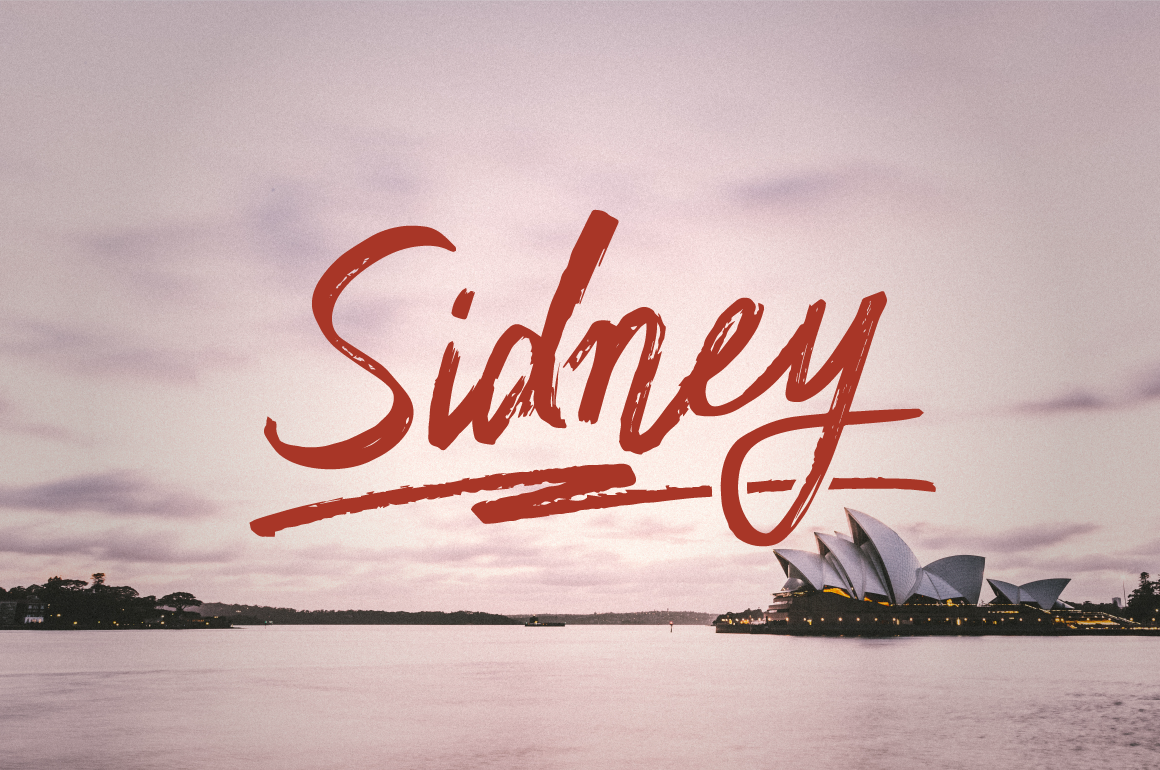
A Sidney Script Font é uma opção única para designers que buscam um estilo elegante e moderno, com uma personalidade intrínseca. Suavemente irregular, esta tipografia oferece 300 formas de letra, ligações e letras extras, criando um universo incrível de combinações únicas. Inspirada no desenho de Hamilton, a Sidney Script é uma fonte script com uma personalidade forte, perfeitamente adaptável para projetos que valorizam o contraste entre limpeza e rusticidade. Além disso, a inclusão dos elementos vetoriais incluídos na versão completa da fonte permite ao designer explorar ainda mais essa paleta única. Pronta para transformar seu próximo projeto de forma inovadora? Instale a Sidney Script Font agora!